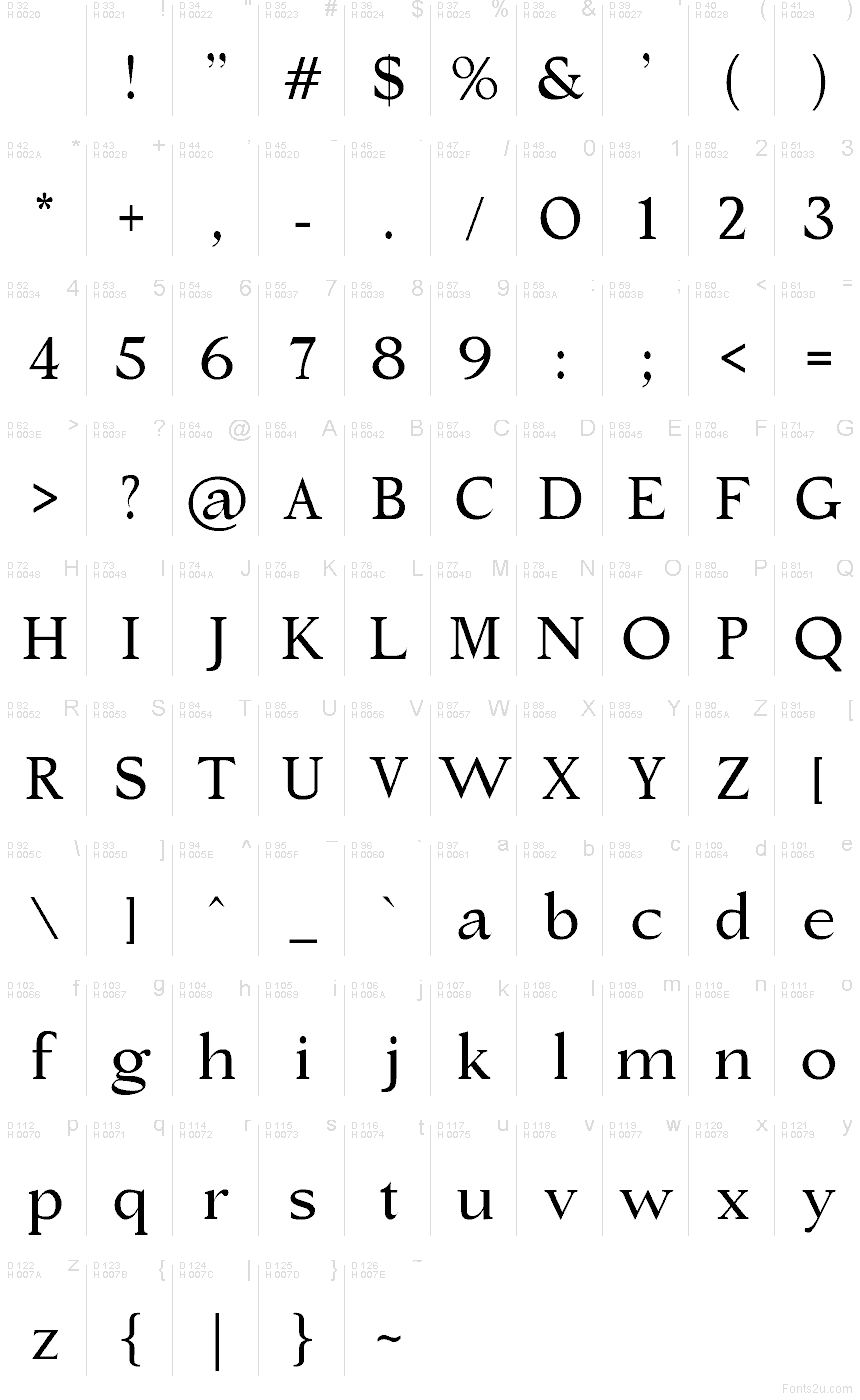
Silent Citadel Light, creata da Muhamad Fikry Nuralif di Fikryal Studio, è un font serif moderno e gratuito appartenente alla famiglia Silent Citadel. Il suo stile fresco e arioso, caratterizzato da tratti sottili e grazie incise, conferisce anche alle brevi linee un'autorità letteraria composta. La spaziatura equilibrata garantisce una leggibilità impeccabile senza compromettere quel fascino austero e d'altri tempi.
Silent Citadel Light assicura risultati eleganti su copertine di libri, titoli editoriali, identità visive per musei o gallerie, packaging di boutique, titoli cinematografici, citazioni e testi di grande impatto per il web. Impostatela con una dimensione leggermente maggiore per la massima raffinatezza e abbinate questo font gratuito a una sans serif neutra come Inter o Helvetica per un contrasto nitido e moderno.